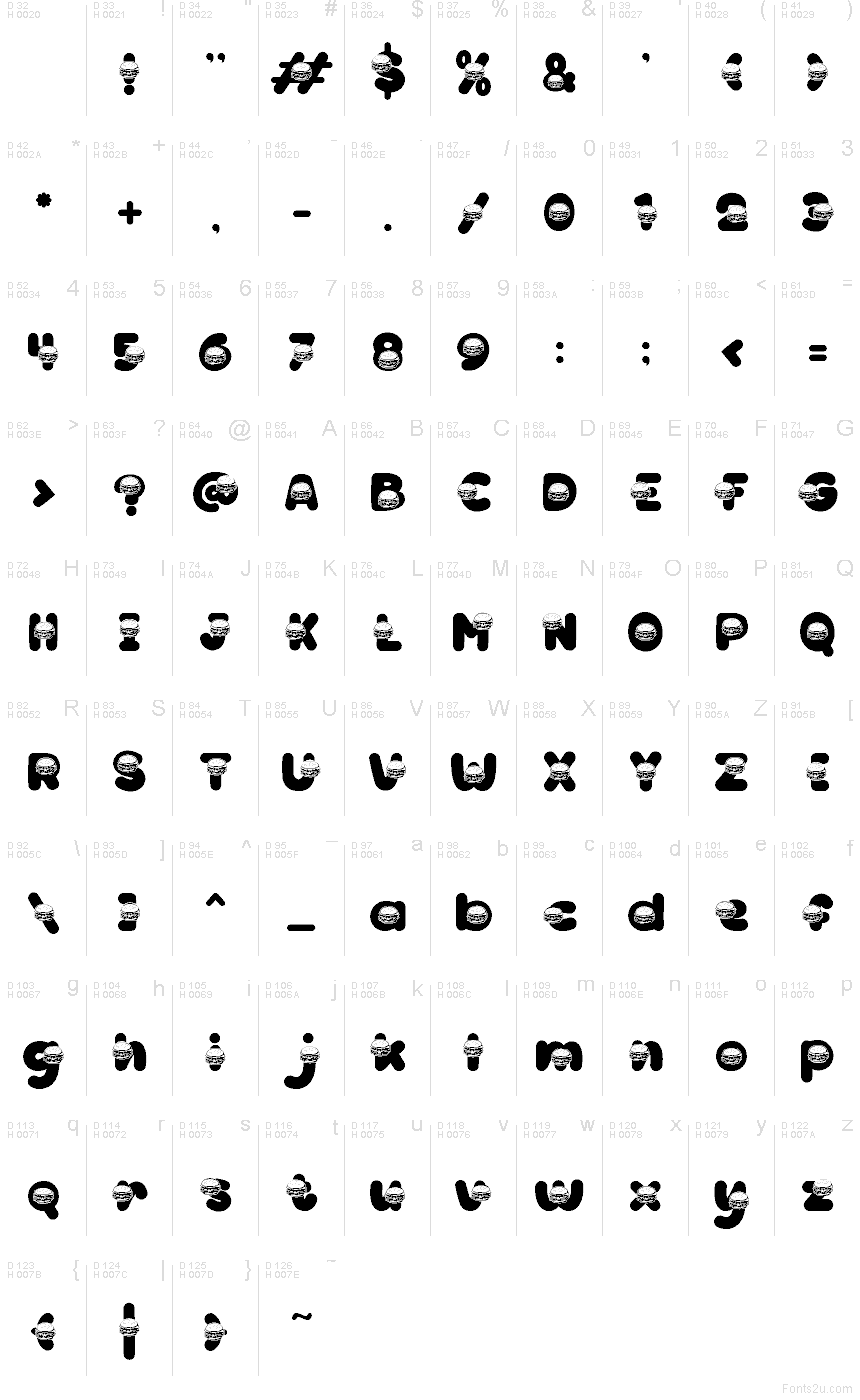
Smoky Maple Four, de Putracetol Studio, es una tipografía display gratuita con temática de hamburguesas, que destaca por su silueta robusta y divertida, con un toque de humor irónico. Las letras están construidas como formas minúsculas suaves y gruesas, puntuadas por ilustraciones de hamburguesas que aparecen dentro y sobre los caracteres, otorgando a toda la fuente ese aire alegre de cartel de comida rápida.
Funciona de forma natural para branding de hamburgueserías, menús, envases de snacks, gráficos de food trucks y redes sociales, donde esta tipografía gratuita puede llevar el peso visual por sí sola. Dado que el motivo de la hamburguesa se repite en las letras en lugar de ser un simple adorno puntual, también es ideal para títulos cortos y logotipos que busquen una personalidad desenfadada y muy apetecible.